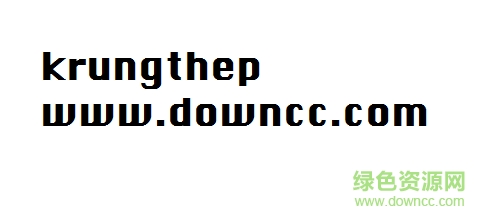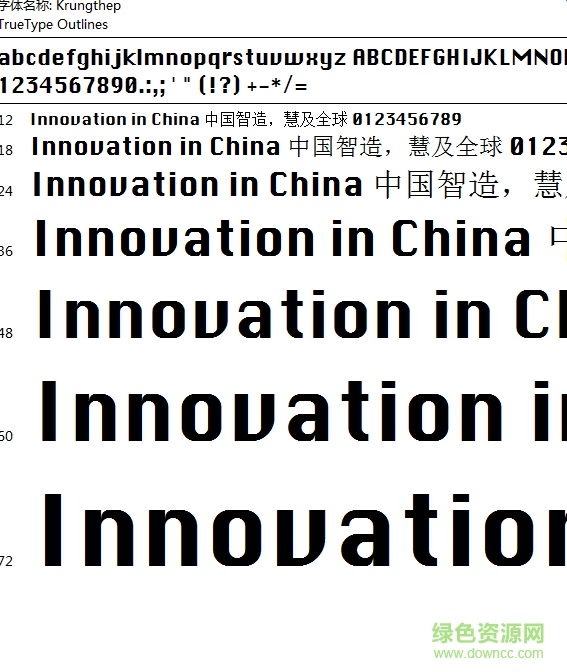
krungthep字體是一款時(shí)尚英文字體軟件,其創(chuàng)意十足的粗黑英文風(fēng)格,深受廣大年輕人喜愛,字體廣泛應(yīng)用于設(shè)計(jì)行業(yè),更多好看字體下載盡在綠色資源網(wǎng)!
krungthep英文字體非常連貫,字體筆畫工整大方,整體效果十分出色醒目,非常好看,喜歡就到綠色資源網(wǎng)下載體驗(yàn)吧!